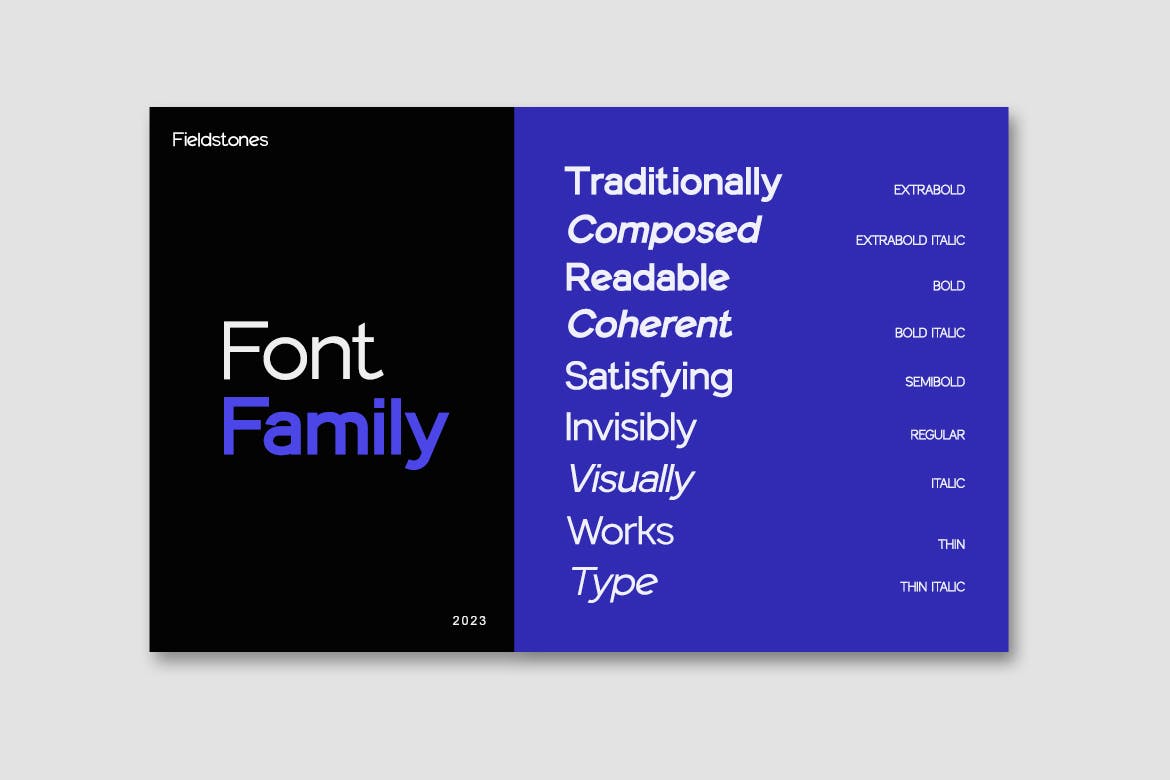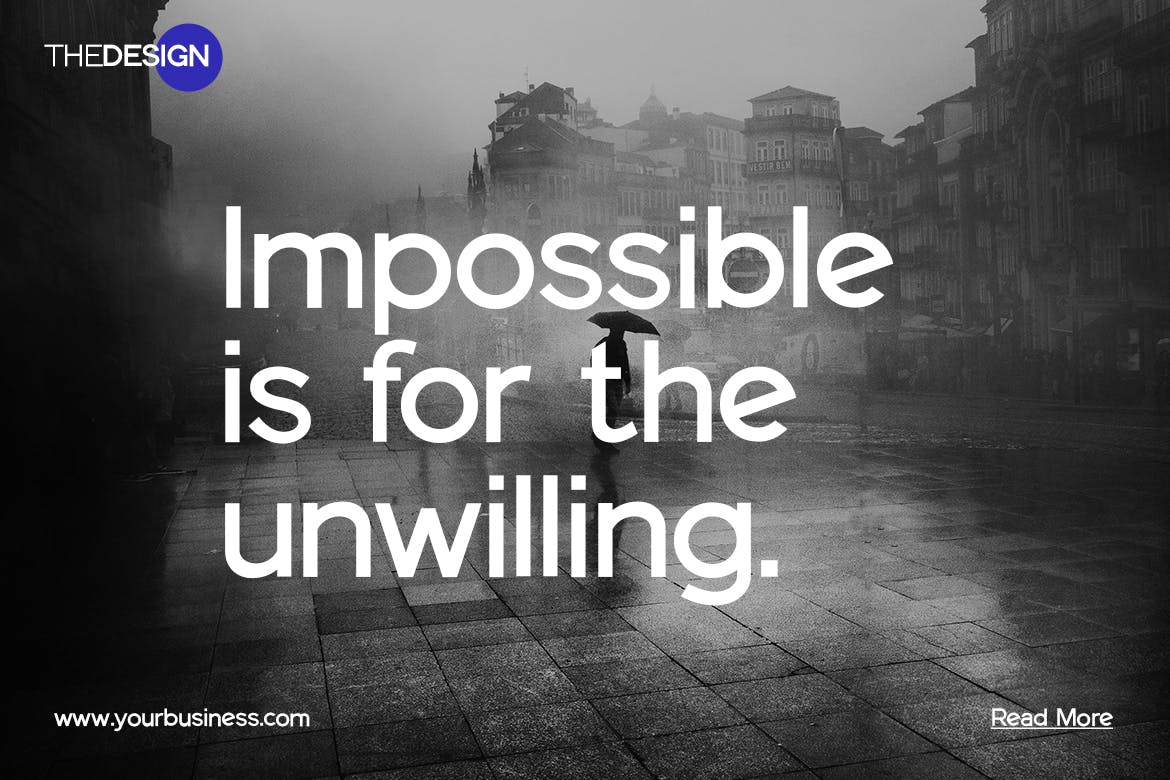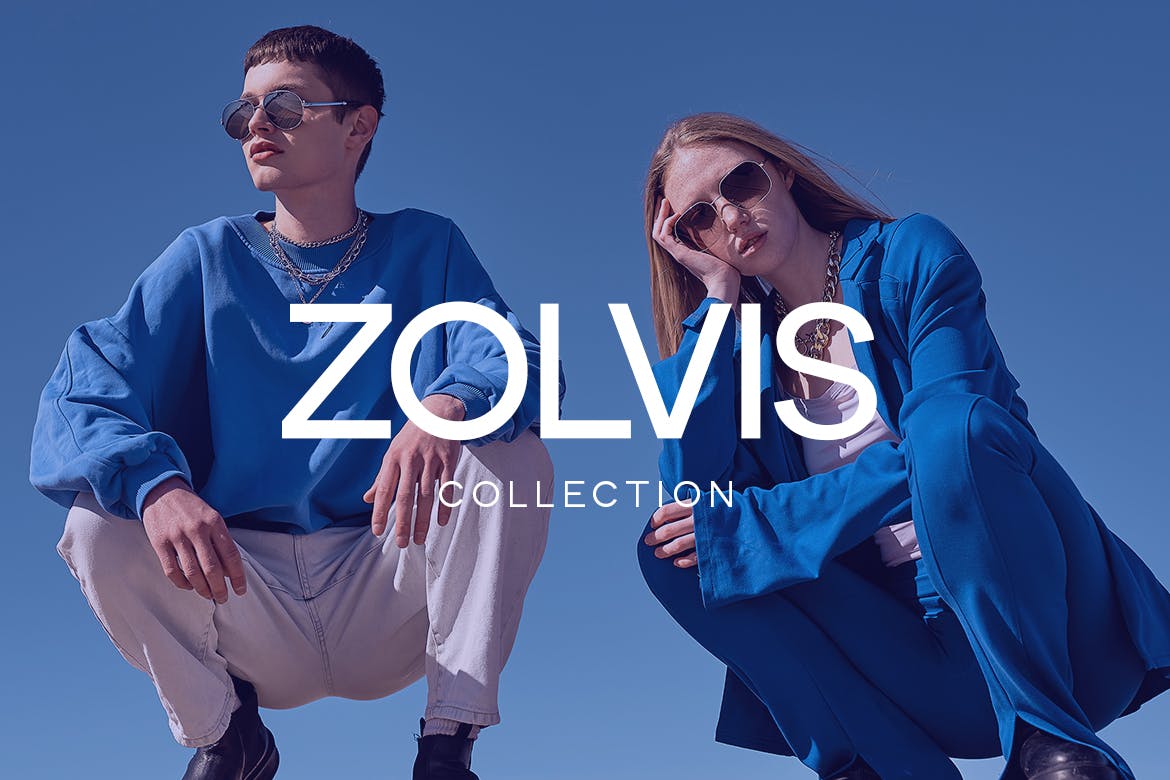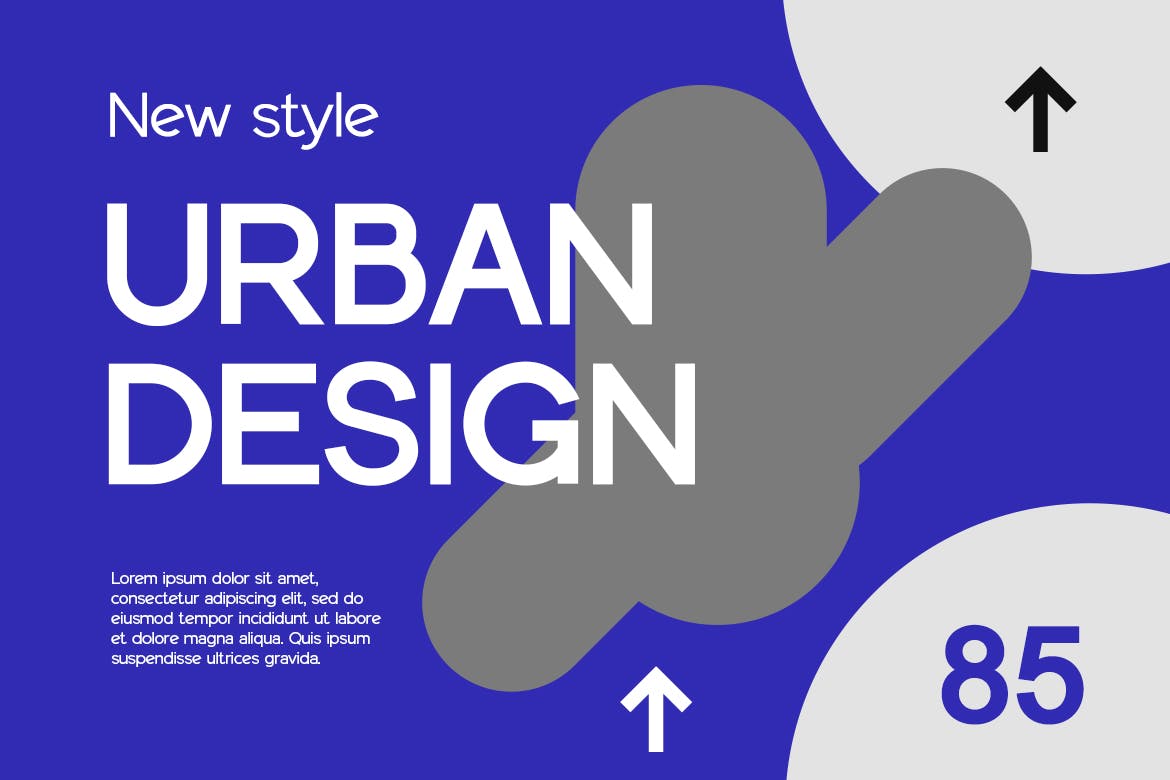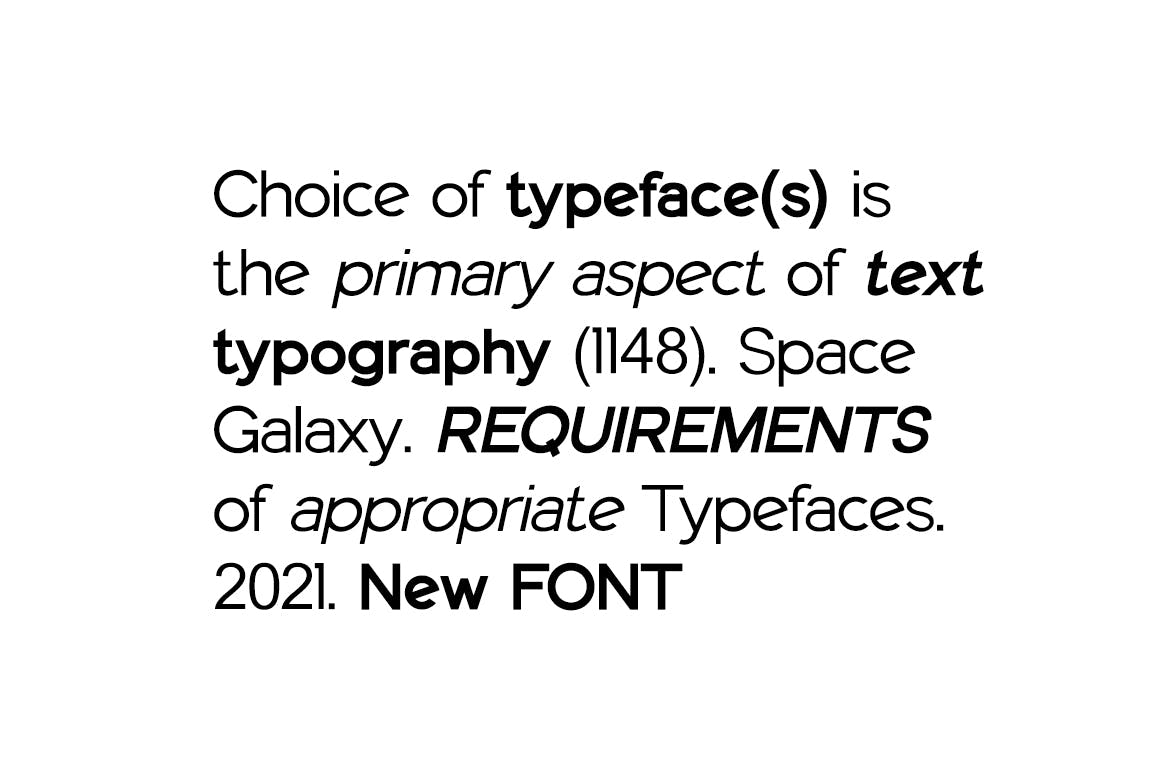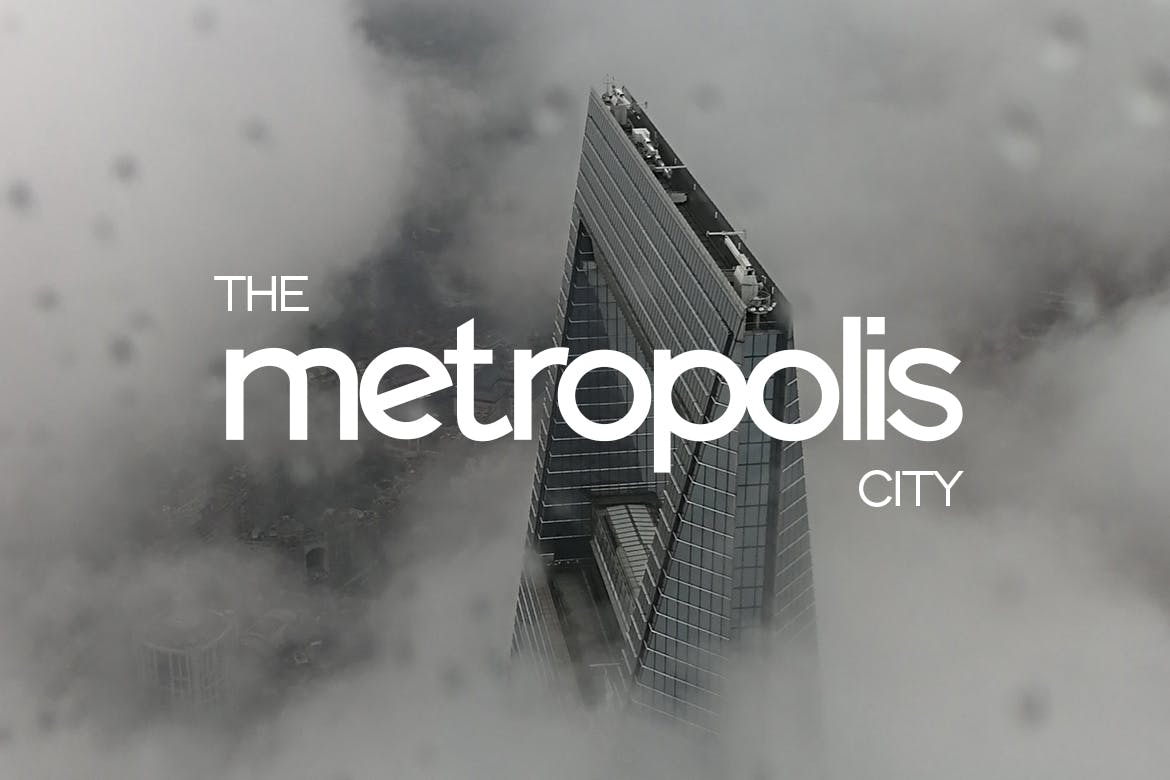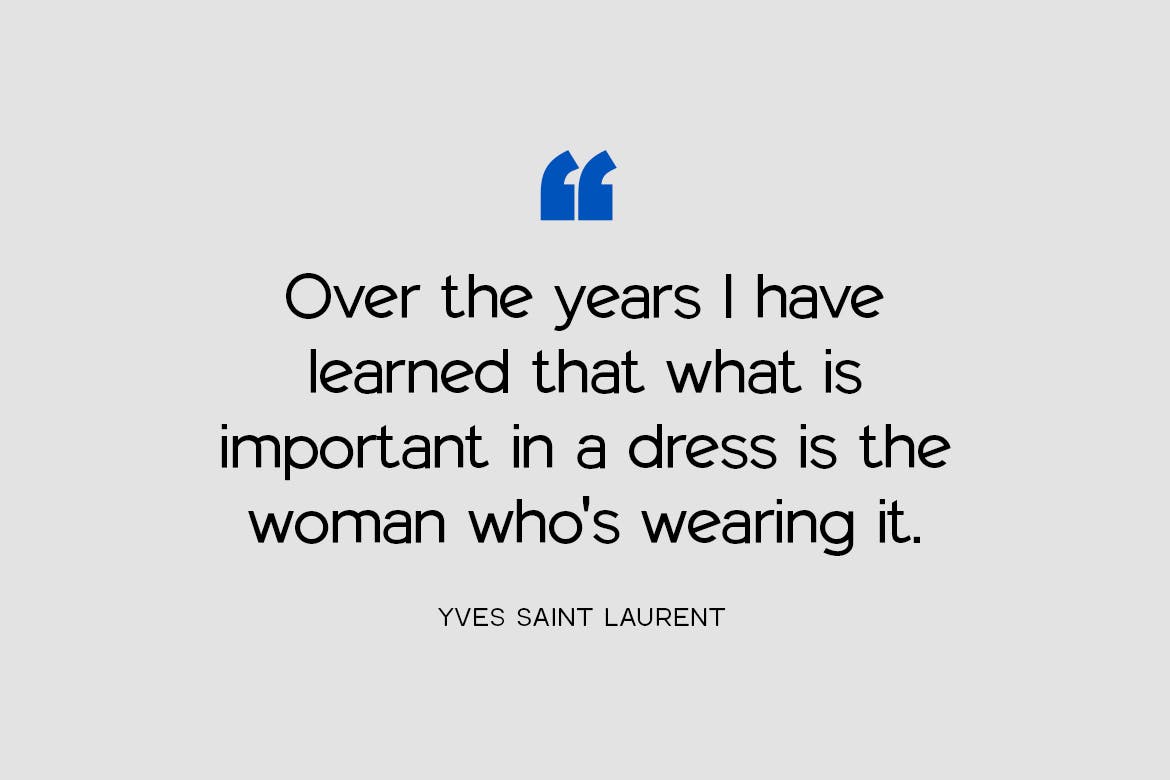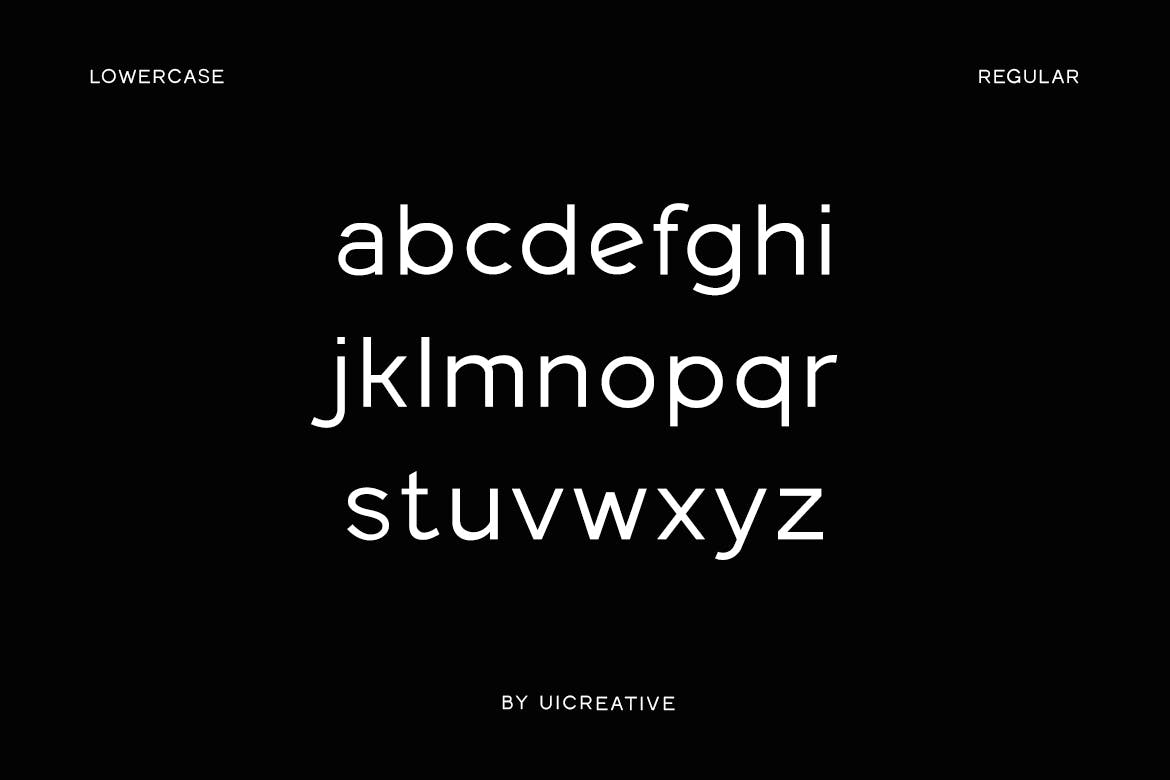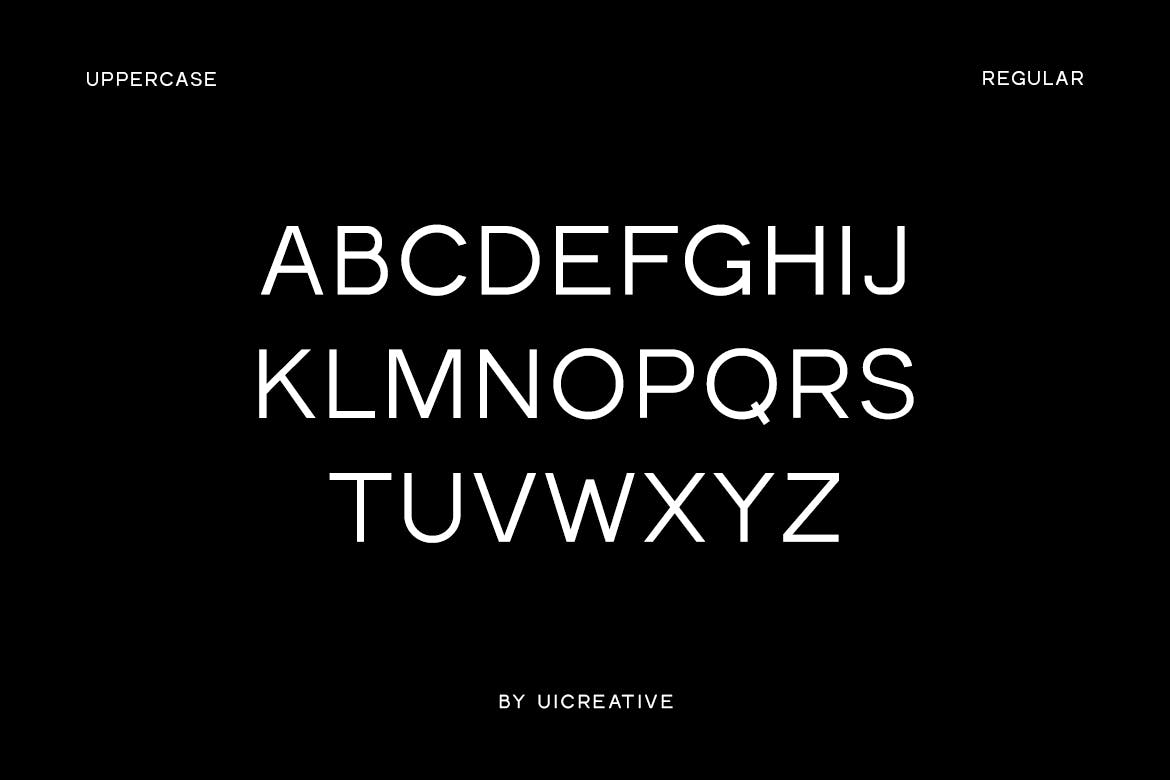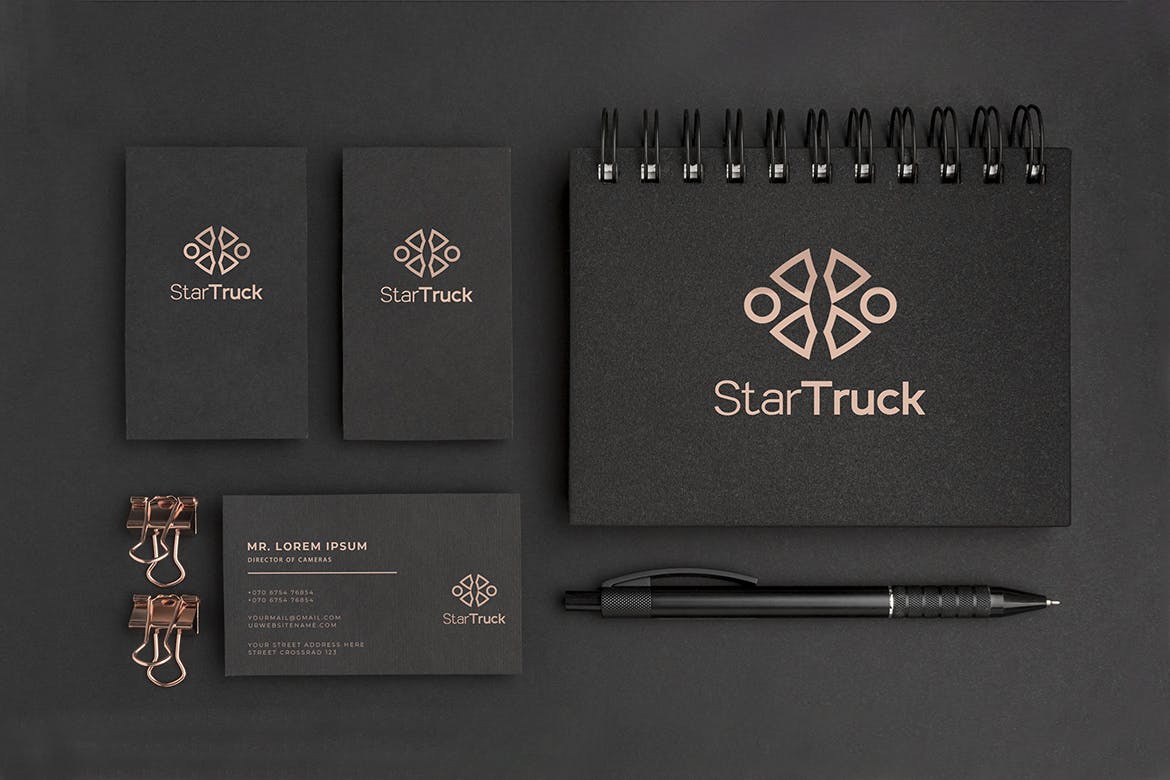
دانلود فونت Fieldstones Modern Sans Serif
Fieldstones Modern Sans Serif Family Font
فونت Fieldstones با طراحی مدرن و شیک، مناسب برای پروژه‌های مختلف.
ما با افتخار فونت جدید خود را به شما معرفی می‌کنیم؛ نام این فونت Fieldstones Modern Sans Serif Family Font است. این فونت احساسی زیبا، کلاسیک، باوقار و مدرن را به پروژه‌های شما می‌بخشد. فونت Fieldstones به‌طور ویژه برای انواع پروژه‌ها، مانند امضا، لوازم‌التحریر، لوگو، مراسم عروسی، نقل‌قول‌های تایپوگرافی، جلد مجلات یا کتاب‌ها، هدرهای وب‌سایت، برندینگ، طراحی بسته‌بندی و موارد دیگر مناسب است. همچنین، طراحی‌های مرتبط با مد و برندینگ نیز ویژگی‌های مردانه و زنانه را به‌خوبی نمایش می‌دهد.